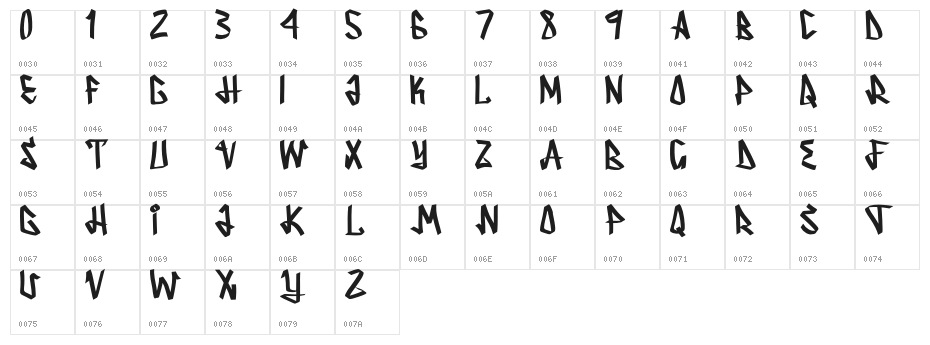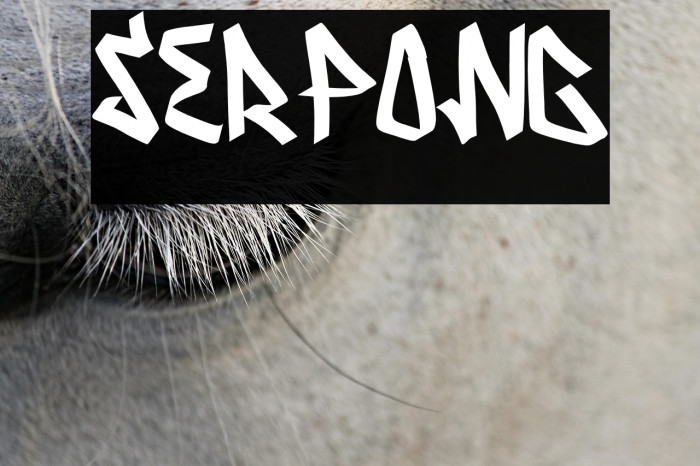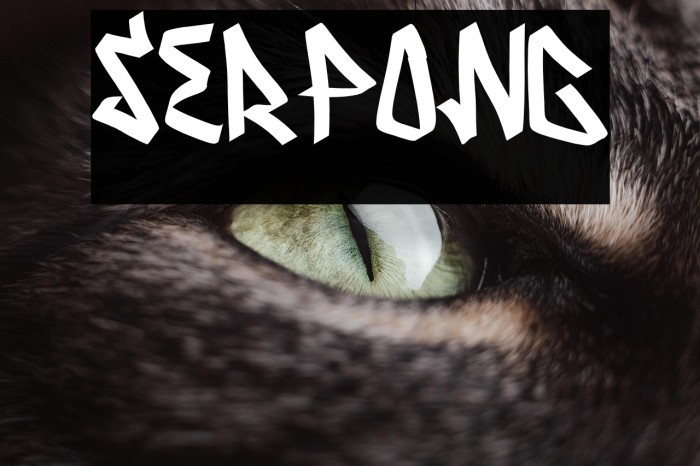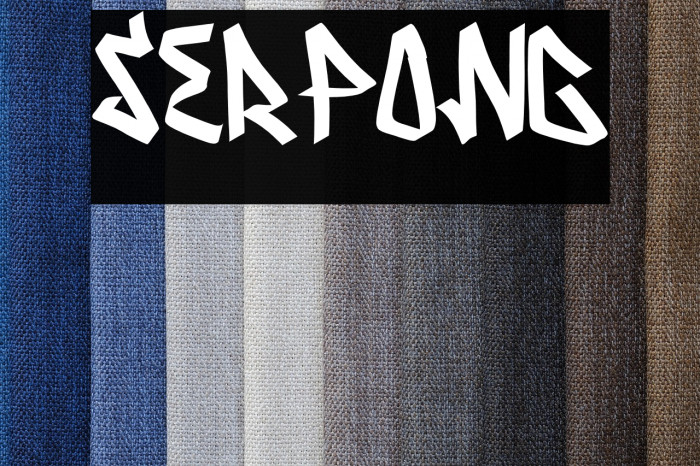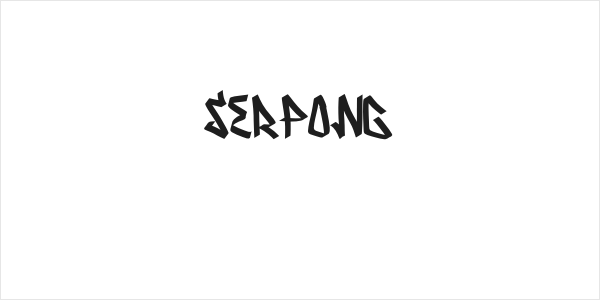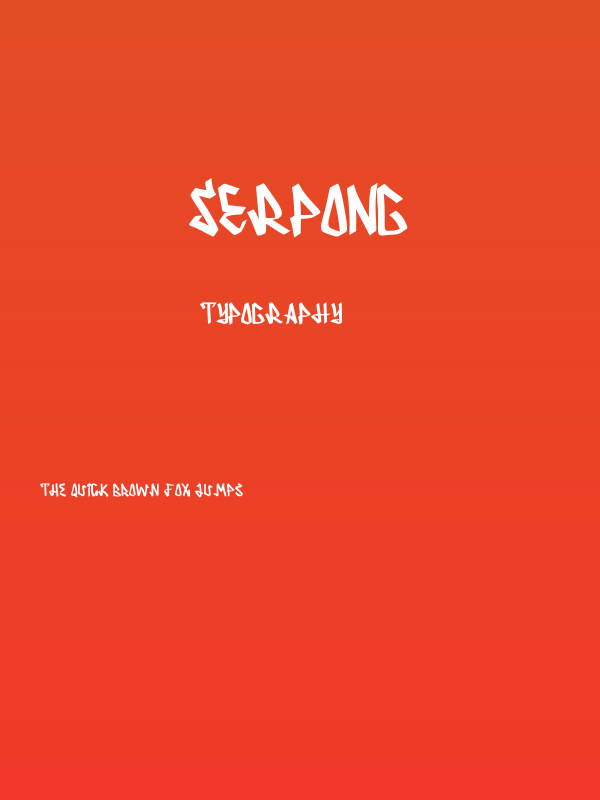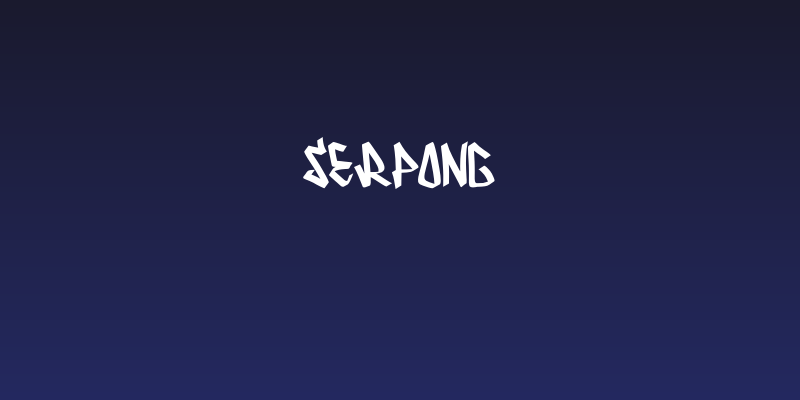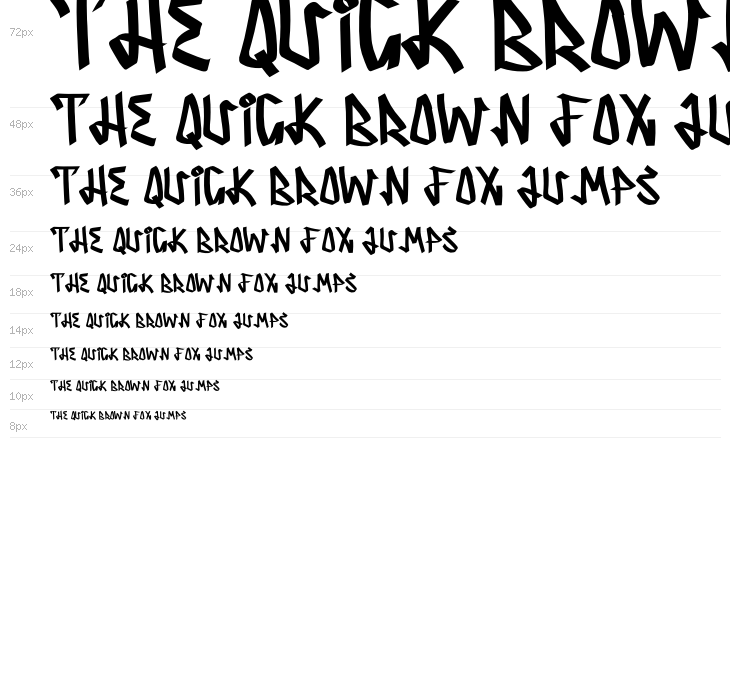
Serpong Font
✎ Graffiti
| Categorie | Graffiti |
| Stile generale | Modern, Urban |
| Progetti proposti | Ideal for street art designs, urban-themed posters, music album covers, and edgy branding projects. |